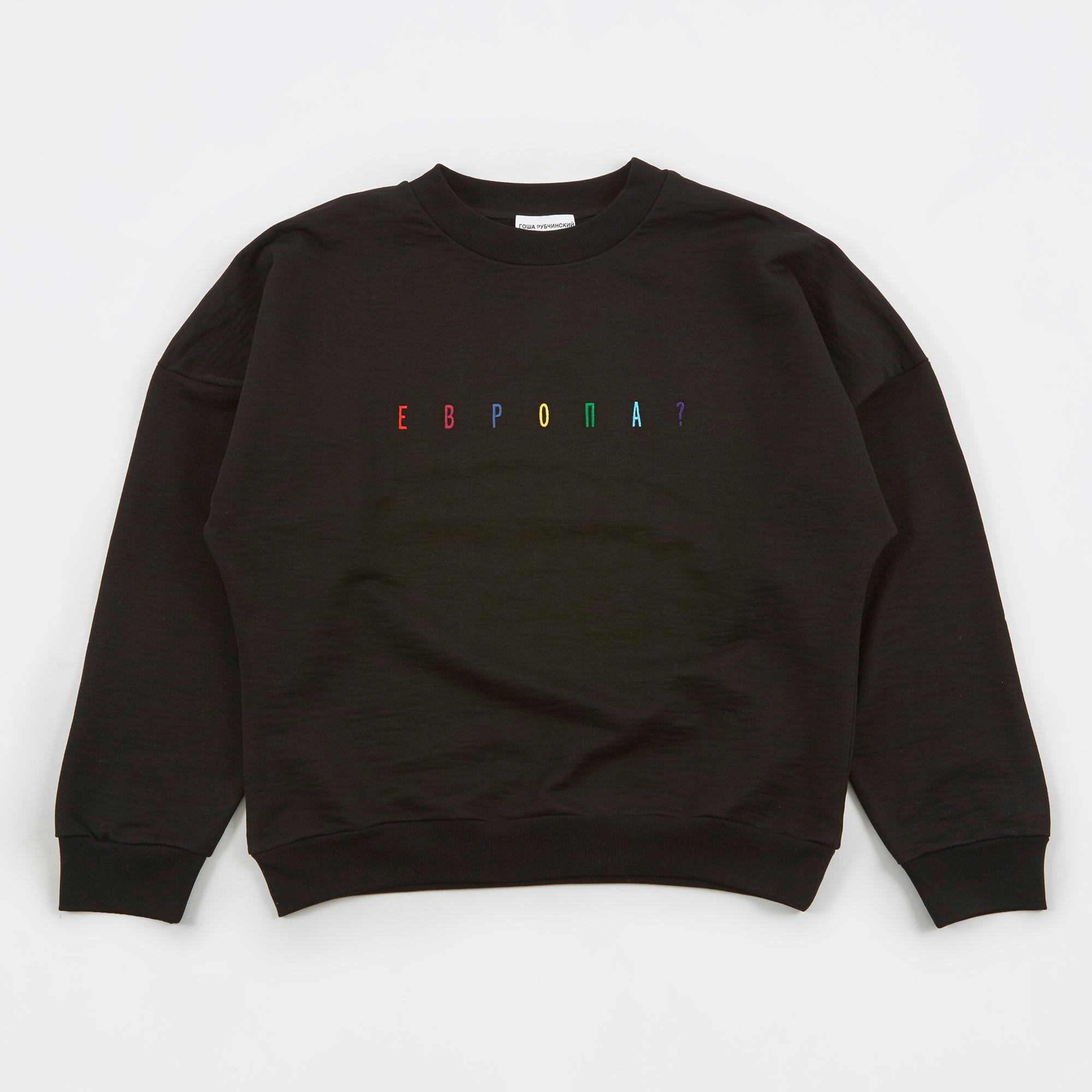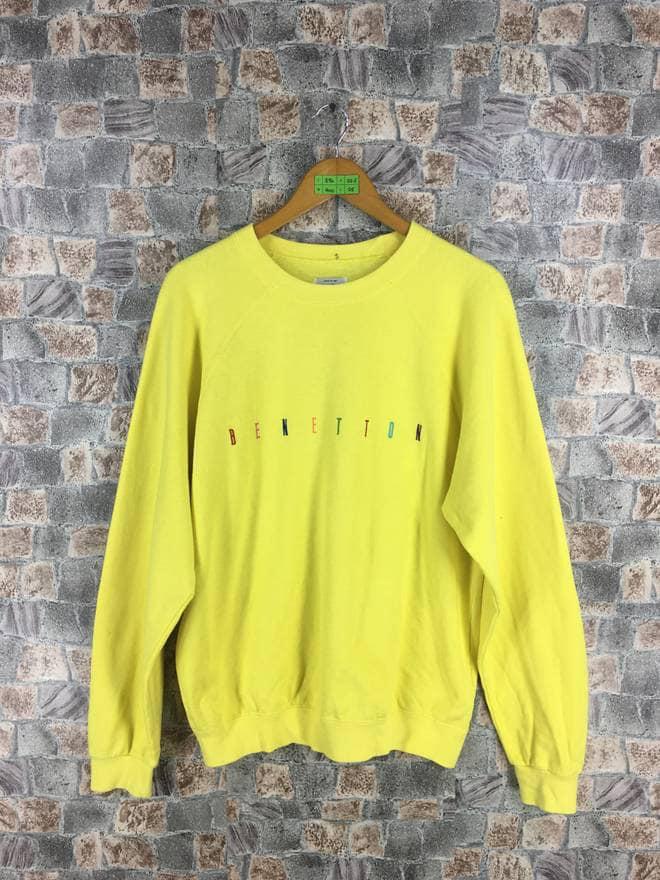
Suche Schrift von Gosha Pullover
Ich bin auf der Suche nach dieser (oder einer ähnlichen) Schrift auf dem Gosha "Europa?" Pullover (Quelle hier):
Abgekupfert wohl von einem alten Benetton Pullover (dort aber nicht so gut zu erkennen):
Die Schrift ist ohne Serifen und sehr hoch. Selbst mit sehr hohem Zeichenabstand und/oder Leerzeichen bekomme ich das nicht mit meinen Schriftarten hin, da bei dieser Buchstabenbreite die Höhe meist deutlich geringer ist.